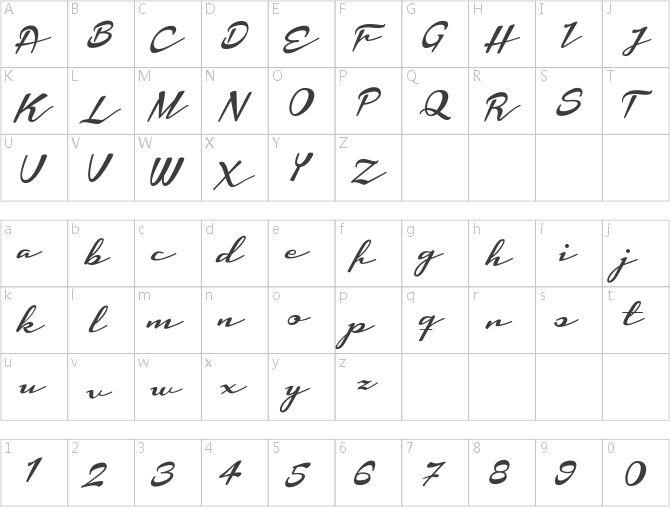
Housegrind Personal Use Only 详情页
Housegrind Personal Use Only
Housegrind Personal Use Only字体字库是一款让人赏心悦目、百看不厌的英文字体,适合各类广告和产品包装设计应用,字体大小0.12MB,格式为ttf字体,上传用户是KISEKI,作者/版权方为未知